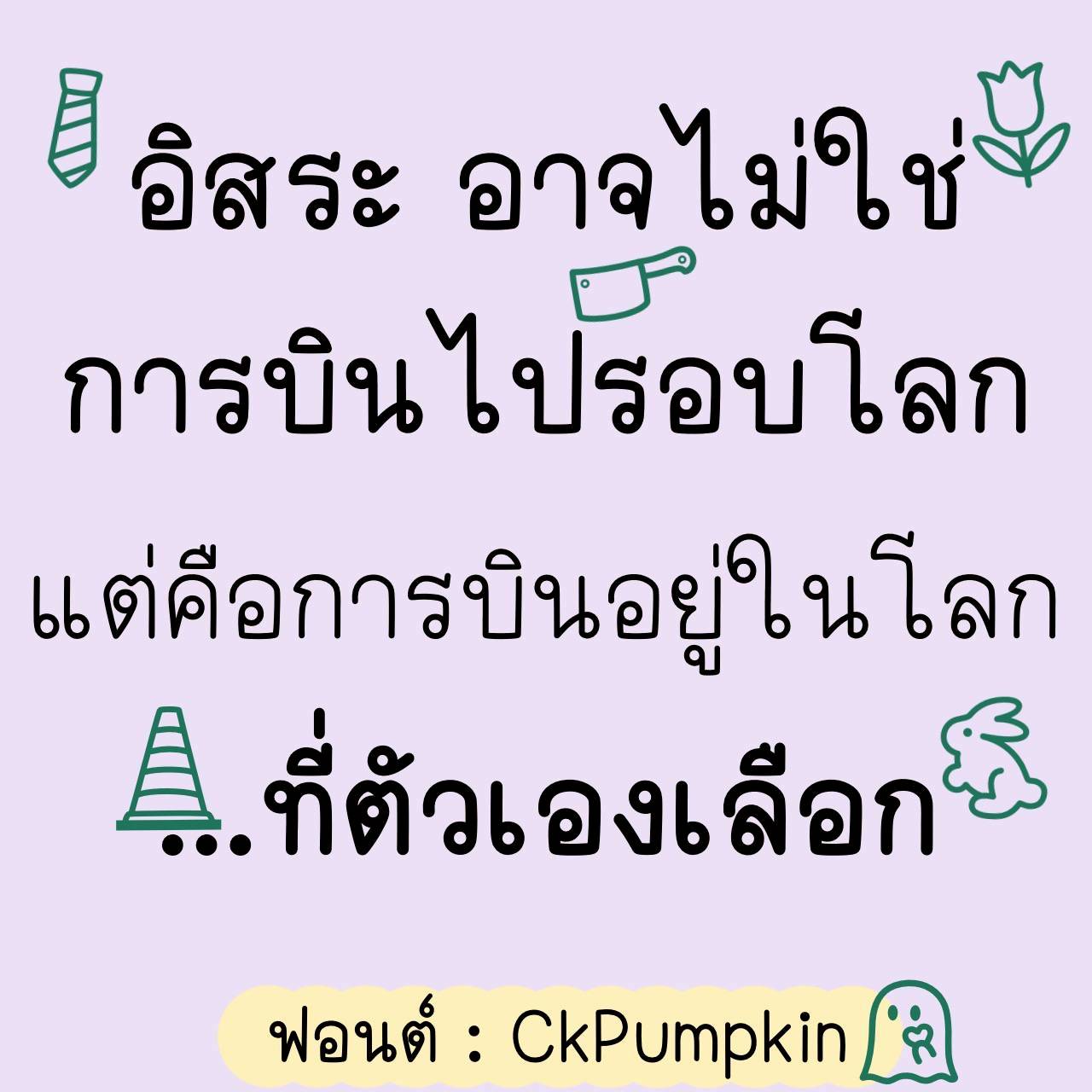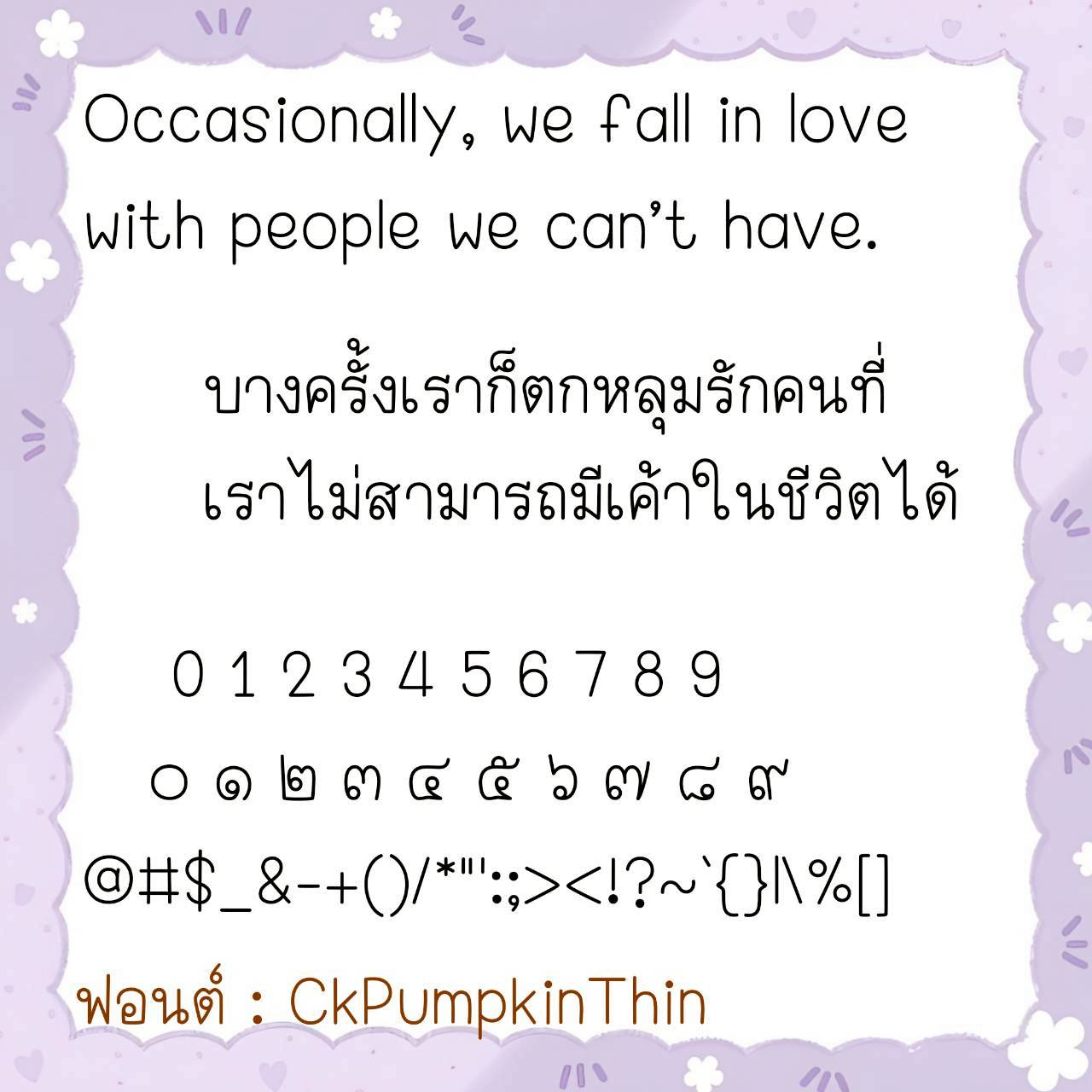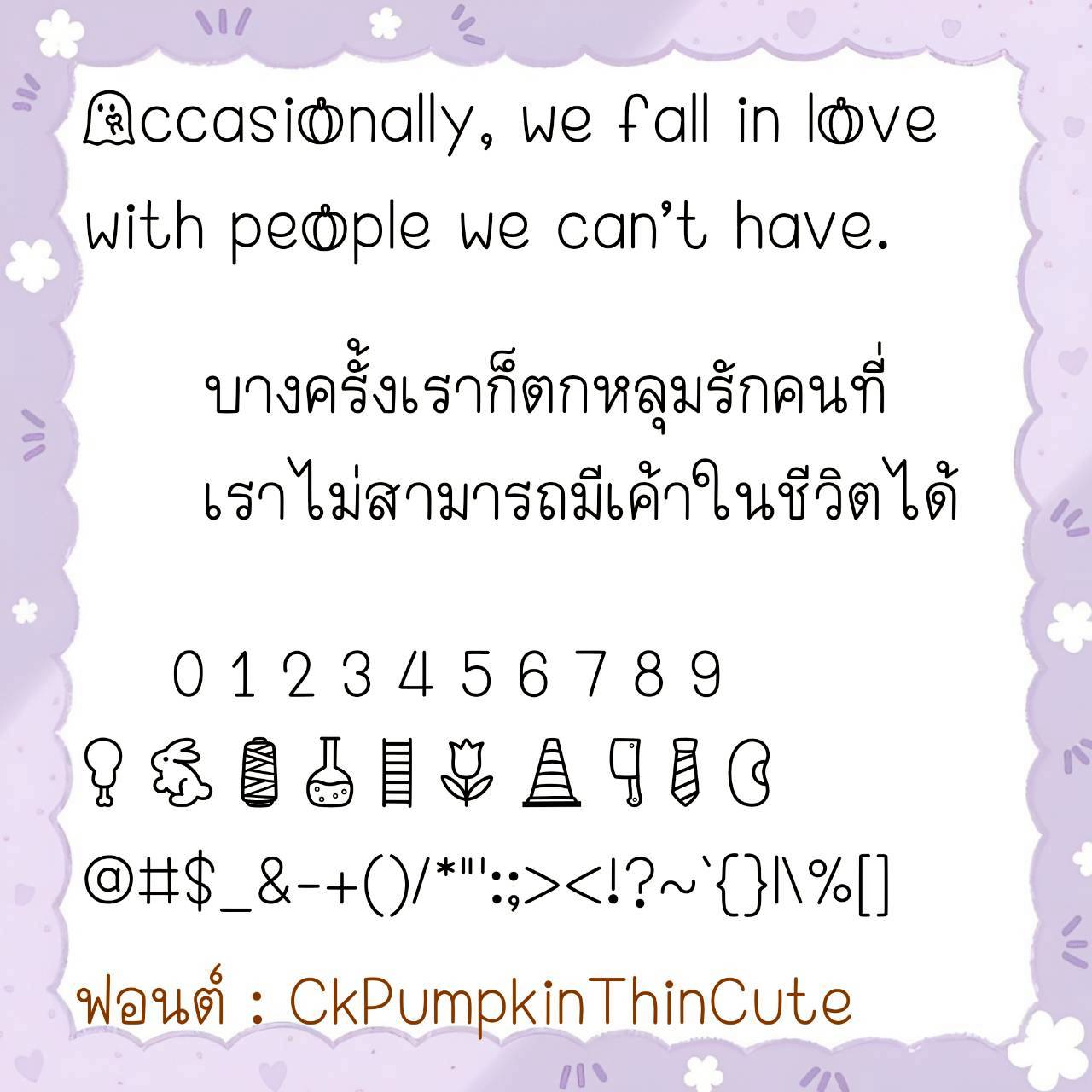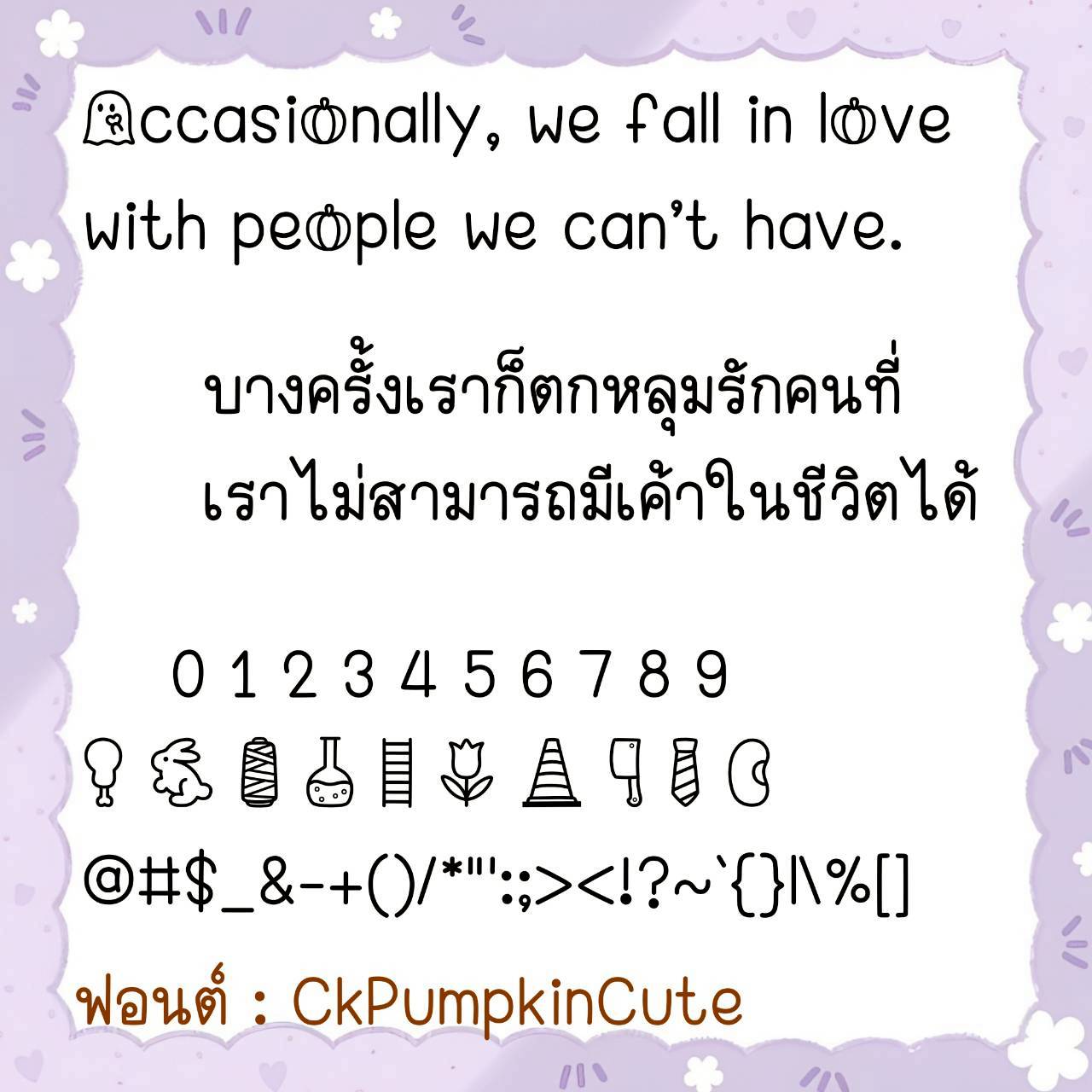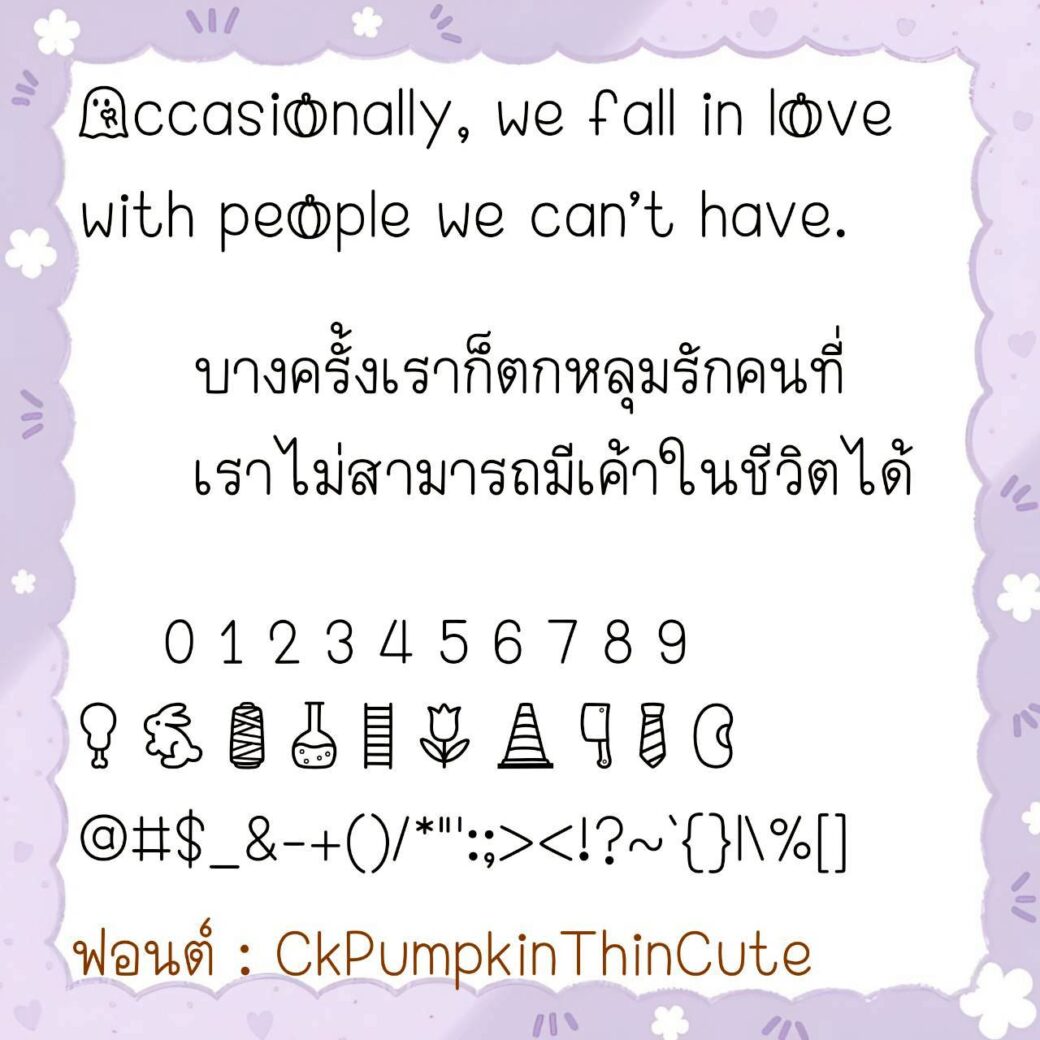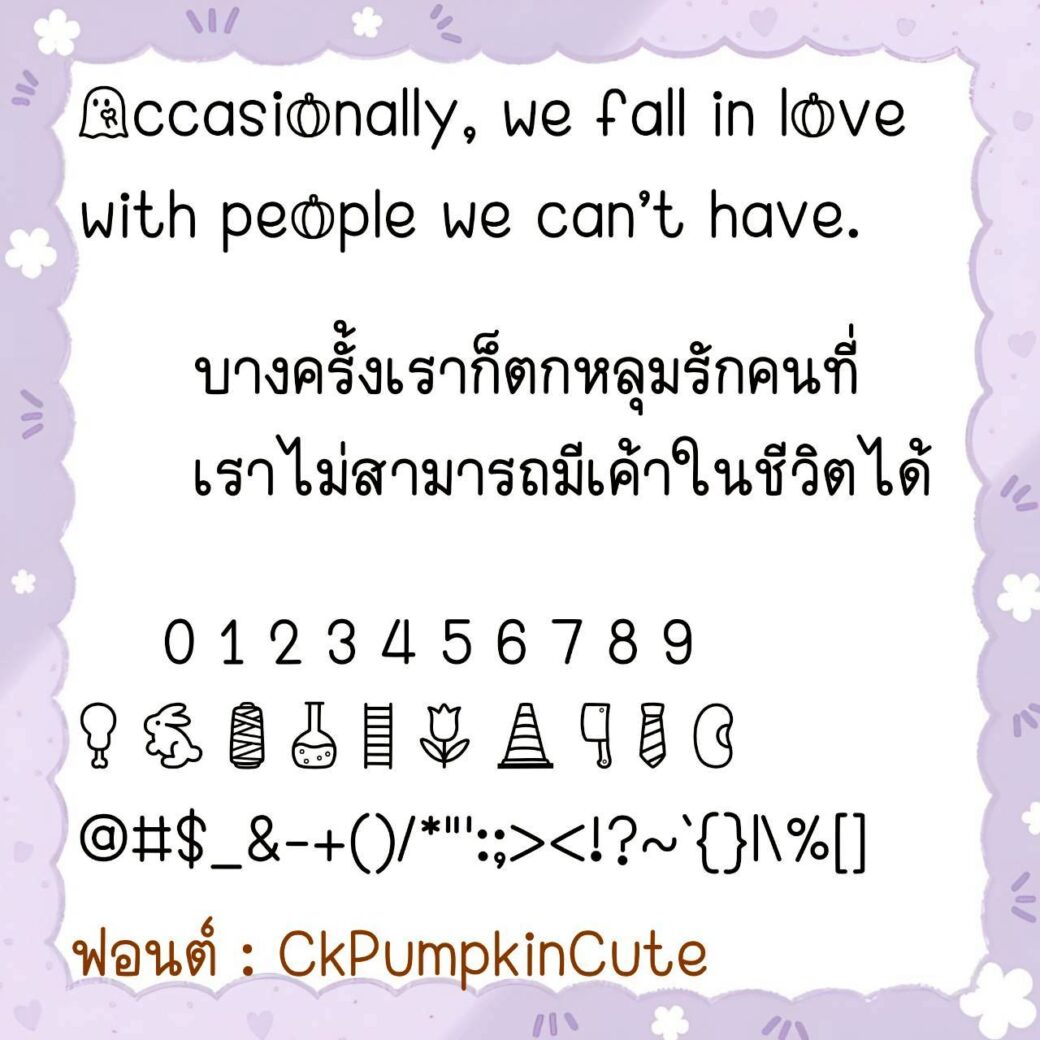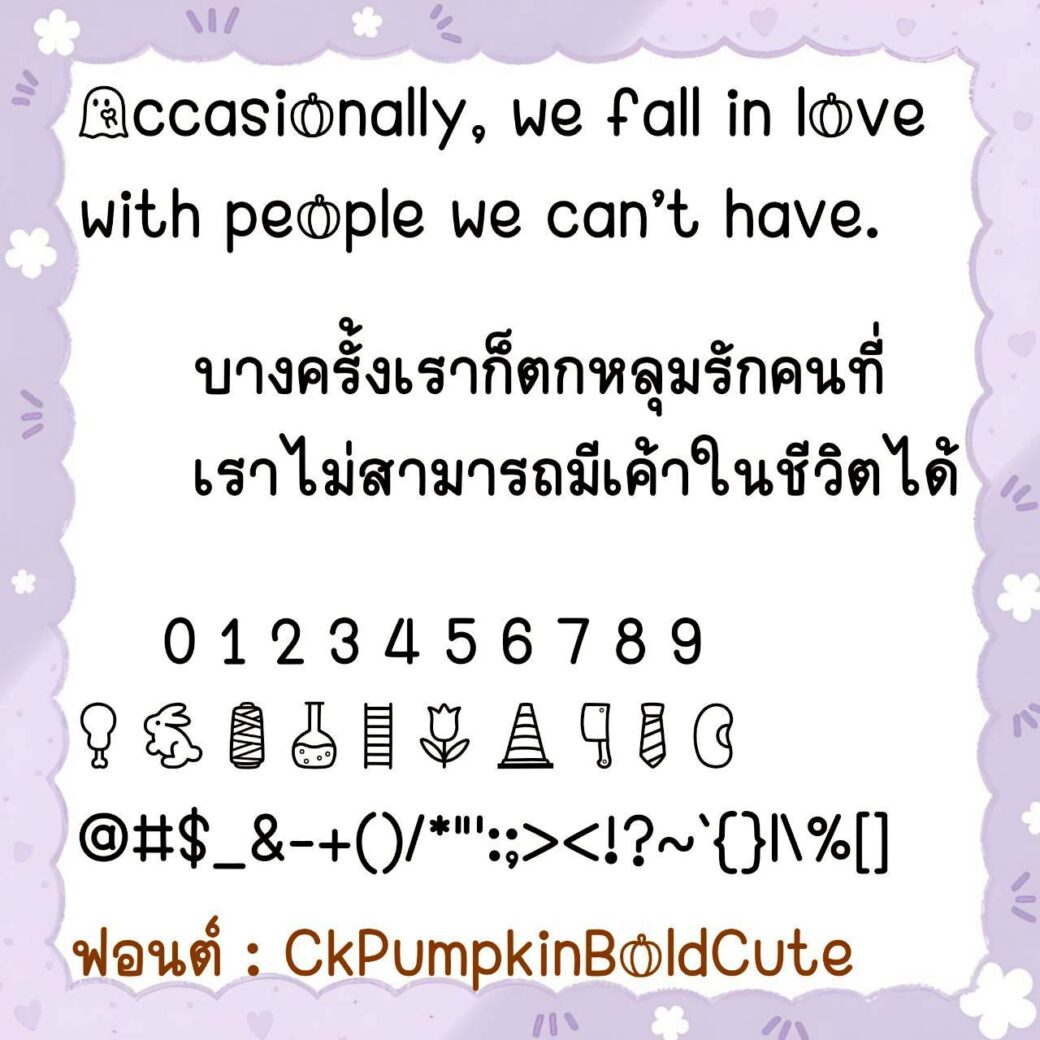
Font CkPumpkin
ชื่อสินค้า : Font CkPumpkin 💙
🔸 ฟอนต์ลายมือแนวเรียบร้อย มีความกึ่งเหลี่ยมแบบไทยๆ เน้นความเป็นระเบียบเรียบร้อย เพื่อให้ดูอ่านง่าย และยังมีไฟล์อิโมจิน่ารักๆ ที่ใช้แทนเลขไทยให้ด้วยค่ะ 🥰💙
🔹 A neat handwriting font with a Thai-style semi-square design. It emphasizes neatness and order for easy reading. It also includes a cute emoji file that can be used in place of Thai numerals. 🥰💙